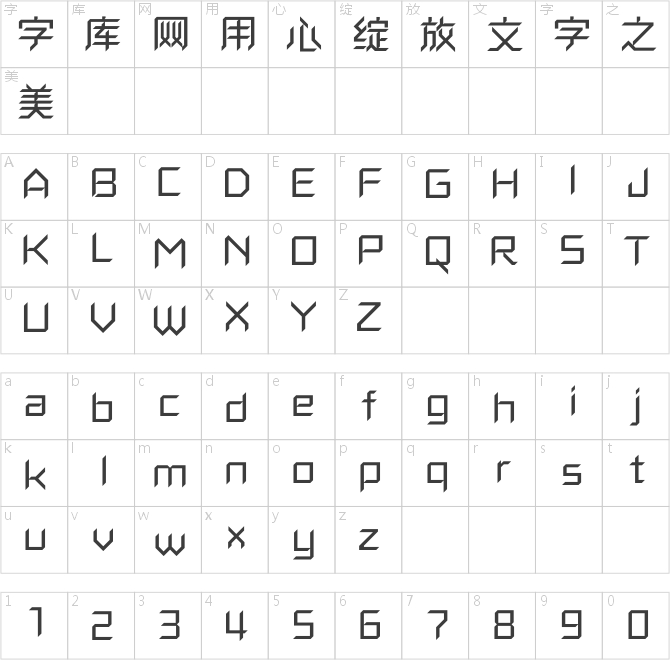
字體名稱: 方正卓越體 簡
方正卓越體 簡 DemiBold
方正卓越體 簡 DemiBold介紹
方正卓越體 簡 DemiBold字體字庫是一款讓人賞心悅目、百看不厭的中文字體,適合各類廣告和產(chǎn)品包裝設(shè)計應(yīng)用,字體大小1.42MB,格式為ttf字體,上傳用戶是15331803325,作者/版權(quán)方為方正字庫